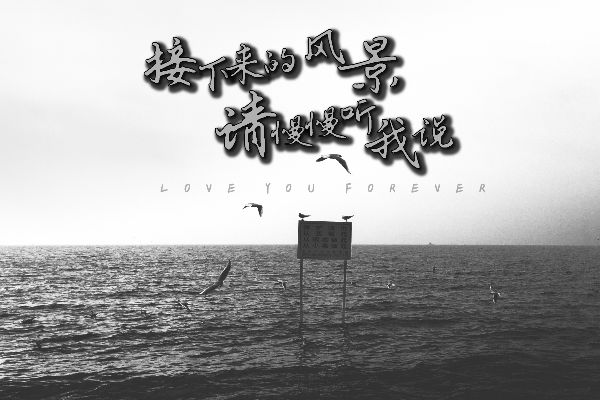
免费的行书字体不好找,本文给你分享3款免费商用的行书字体
行书,作为中国书法的一种重要字体,以其独特的风格,在物料的设计时,受到了很多设计师的喜爱。
那么,行书究竟是什么?它是否可以用于商业用途?有哪些免费的商用字体可以选择?又有哪些需要授权的商用字体?本文就逐一给你答案。
一、 行书是什么字体?
行书,是在楷书和草书之间一种过渡性的字体。 它的出现,是为了解决楷书过于工整、书写速度慢,而草书又过于潦草、不易辨认的矛盾。行书在保留楷书基本结构和笔画的基础上,通过笔画的连写、省略、变形等方式,大大提高了书写效率,同时又保持了较好的可读性。
行书的特点可以概括为:
- 既有楷书的端庄,又有草书的流畅。
- 笔画之间常常相互连接,形成“笔势”。
- 在保证可读性的前提下,对笔画进行适当的简化和变形。
- 书相较于楷书,书写速度更快。
- 连笔和笔势的运用,使得行书具有很强的节奏感和流动感。
三、 3 款可以免费商用行书字体
云峰静龙行书
云峰静龙行书如云峰般飘逸,似静龙般舒展,笔画流畅,姿态灵动,将行书的洒脱与龙的威仪巧妙融合。
适合场景:
- 品牌Logo设计
- 海报、宣传册封面
- 书法作品、艺术创作
- 高端礼品包装
鸿雷行书简体
鸿雷行书简体,如同奔腾的雷电,充满力量与速度感。笔画粗犷有力,结构紧凑,展现出一种疾风骤雨般的激情
适合场景:
- 体育赛事宣传
- 摇滚音乐海报
- 游戏宣传片标题
- 促销活动的醒目标题
钟齐志莽行书
钟齐志莽行书,风格豪放不羁,笔画粗犷有力,字形饱满,透露出一种“志存高远,气势恢宏”的意境。
适合场景:
- 企业品牌Logo(尤其制造业、建筑业)
- 历史文化类宣传
- 户外广告牌
- 传统工艺品包装
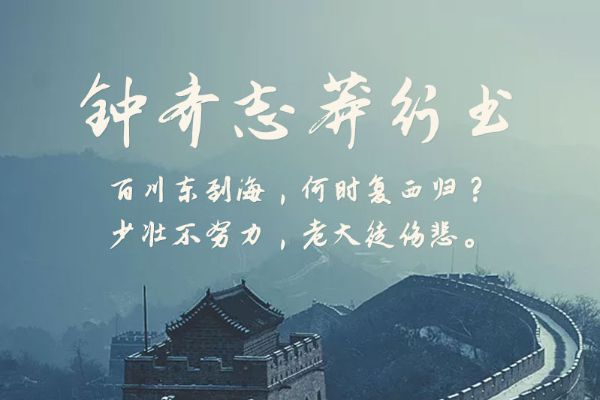
四、 5 款可以会员商用行书字体
字家琉璃行书
字家琉璃行书,如琉璃般晶莹剔透,光彩照人。笔画流畅灵动,字形优雅,散发出一种精致、高贵、温润的气质。适合用于需要体现优雅、细腻、艺术性的设计。
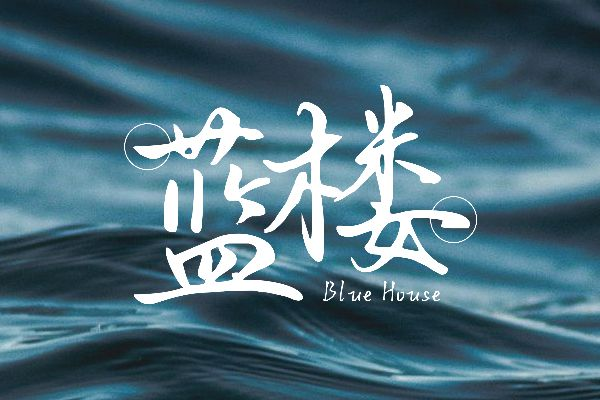
点字龙飞行书
点字龙飞行书,将点画的灵动与龙的腾飞之势相结合。笔画虽为点,却能勾勒出龙的筋骨,字形轻盈而有力,充满动感与想象力。适合表现创意、活力、不拘一格的风格。能为设计增添一份独特的艺术气息。
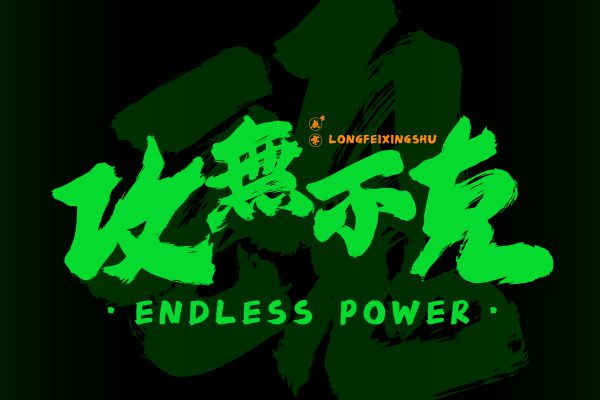
叶根友畅行书
叶根友畅行书,以其流畅自然的笔触,传递出一种舒展、洒脱、畅快淋漓的书写感受。字形清晰易读,又富于变化,兼具实用与美观。可读性强,适合大量文字的排版。能够满足商业应用中的多种需求。
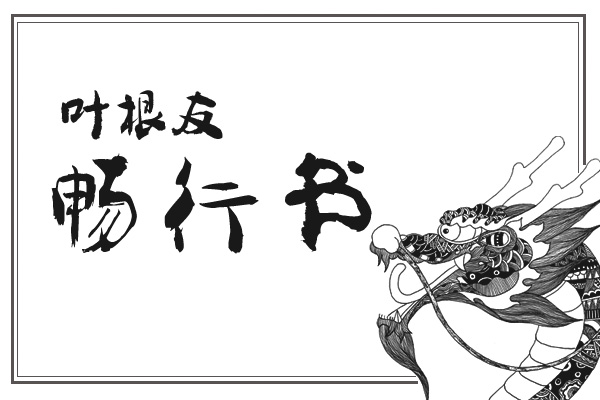
心悦君行书体
心悦君行书体,字如其名,以一种温婉、喜悦、心意相通的笔触书写。字形柔和,笔画舒展,传递出一种真挚的情感与美好的祝福。适合用于表达情感、传递祝福的场景。比如贺卡、请柬设计、婚礼等。
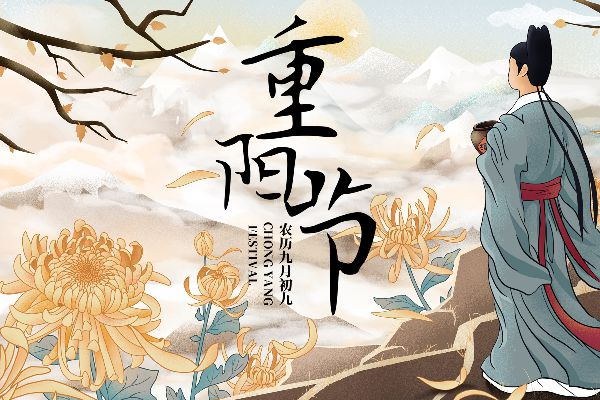
汉呈王世李行书
汉呈王世李行书,融合汉字之美与王羲之行书的风骨。笔画遒劲,结构严谨,又带有行书的灵动飘逸,展现出一种古韵悠长、气度不凡的书法魅力。适合用于需要体现文化、历史、品位的项目。比如:文化古迹宣传、历史题材作品、传统文化活动等。